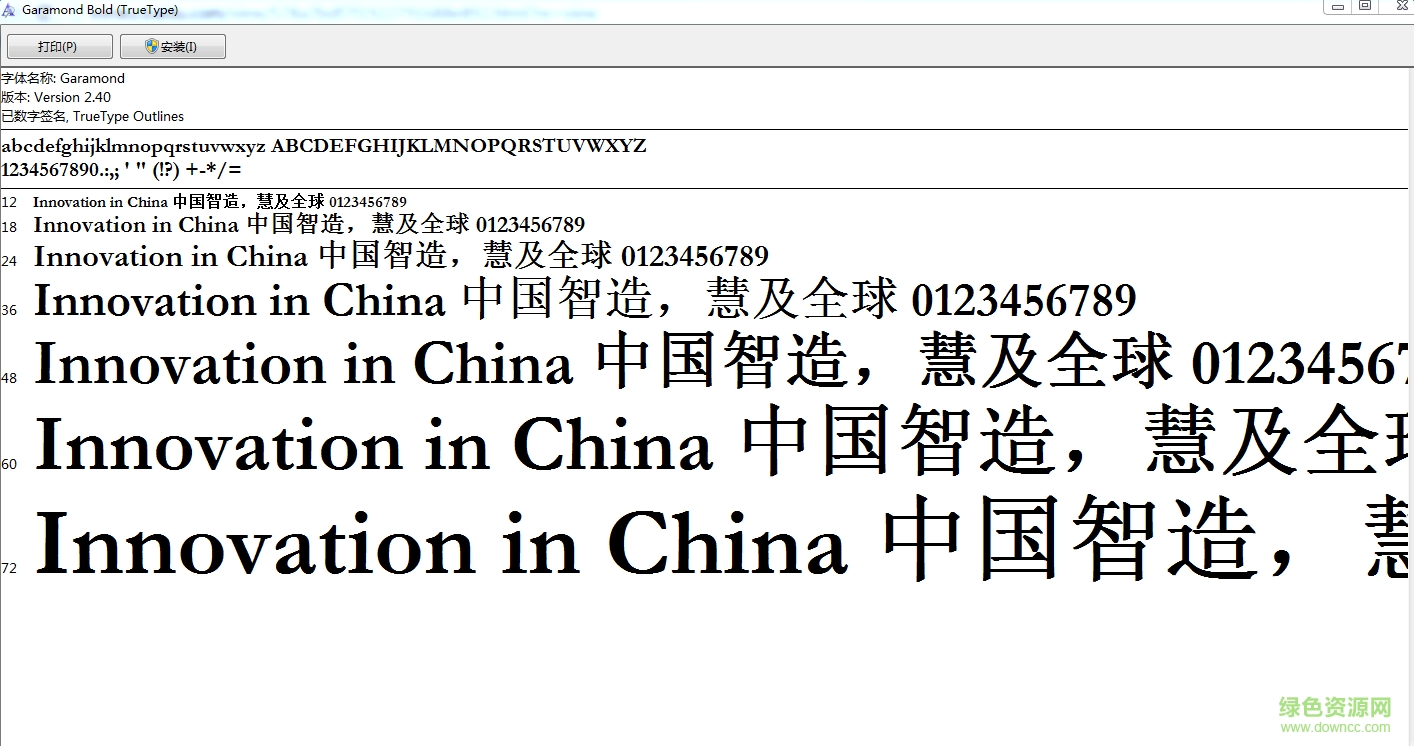
garamond bold字體是一款襯線筆畫自然的英文字體,該字體末端圓潤,線條雖粗卻又不失靈動(dòng),看上去古典優(yōu)雅,喜歡這款字體的朋友可以在綠色資源網(wǎng)免費(fèi)下載!
Garamond演繹出許多優(yōu)美的字體,1964年出現(xiàn)的Sabon是其中最流行的一種。高級餐廳的Menu和高檔紅酒的酒標(biāo)上,都常見到這個(gè)古典而優(yōu)雅的字體?!敖谈浮睂?dǎo)演科波拉在Napa有個(gè)漂亮的葡萄酒莊Niebaum-Coppola,它的網(wǎng)頁可說是Sabon這個(gè)字體最好的使用范例了。